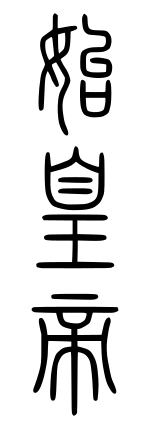
篆書体
篆書体(てんしょたい、モンゴル語:ᠭᠣᠷ
ᠦᠰᠦᠭ᠌[1]、満洲語: ᡶᡠᡴᠵᡳᠩᡤᠠ
ᡥᡝᡵᡤᡝᠨ[2] 転写:fukjingga hergen)は、漢字やモンゴル文字、満洲文字の書体の一種。「篆書」「篆文」ともいう。
広義には秦代より前に使用されていた書体全てを指すが、一般的には周末の金文を起源として、戦国時代に発達して整理され、公式書体とされた小篆とそれに関係する書体を指す。
字形の変化
金文から更に字形の整理が進み、一文字の大きさが均等になった。文字の形は天地が長い長方形の辞界に収まるように作られる。点画は水平・垂直の線を基本に、円弧をなす字画はすみやかに水平線・垂直線と交差するように曲げられる。画の両端は丸められ、線はすべて同じ太さで引かれる。
評価
上記の特徴から、金文と違って上下左右の大きさのバランスが整っており、謹厳な印象を与える文字に進化している。一方曲線を主体とするため有機的な趣きを併せ持ち、独特の雰囲気を持つ書体となっている。
また、後世の漢字のようにへんとつくり、かんむりとあしのように部首分けが容易なのも特徴である。
歴史と展開
起源
小篆の起源は、一般的には中国最古の石刻である戦国期の「石鼓文」に用いられた書体・大篆が直接の起源と言われている。「大篆」は西周の宣王の時代、太史・籀(ちゅう)が公式文字・籀文を定めた際に編纂した書物の名であると伝えられ、籀文そのものの別名であるとされている。このようなことから、石鼓文の大篆は籀文が戦国時代の秦で受け継がれたものと考えられているが、その詳細には諸説ある。
秦による公式書体化
紀元前221年、秦は中国統一を成し遂げた。この際、法治の確立や度量衡の統一の他、文字の統一が行われ、小篆が正式に統一書体として採用された。小篆は始皇帝が李斯に命じて籀文(もしくは大篆)を簡略化したもの、あるいは李斯の進言により当時の秦で行われていた籀文由来の文字を採用したものともいわれる。
始皇帝はこの小篆を権力誇示の手段として用いた。元々甲骨文の時代から文字は権力の象徴であり、それを引き継いでのものである。現に自分を讃える銘文を刻んだ「始皇七刻石」を国内6カ所に立て、大いにその権力を示した。
また小篆は秦が「統一された法治国家」であることを示すため、国の公式証明手段としても用いられた。度量衡の統一の際、決まった大きさの分銅や枡が標準器として全国に配布されたが、これに「権量銘」と呼ばれる小篆を用いた証明文が、金属製の場合直接刻み込まれ、木製の場合銅板に刻まれて貼りつけられた。また、官吏が公式証明に用いる官印にも用いられた。
こうして小篆は秦の国内政策の第一線を担う存在として扱われたのである。
隷書への展開と衰微・変質
そのような国の意図とは裏腹に、小篆はすぐにその形を崩し始める。法治国家である秦では、下層の役人が現場で事務処理を行うことが多くなった。彼らにとって複雑な形をした小篆はきわめて書きづらいものであり、自然走り書きが多く発生する結果となった。このことが小篆の書体の単純化・簡素化を生み、やがて隷書を生むことになるのである(隷変)。
紀元前206年に秦が滅亡すると、楚漢戦争を経て前漢が立った。前漢とそれに続く後漢では公式書体として小篆ではなく隷書が採用されることになったが、このことには小篆の煩雑さを避けるためという意図があった。またこのような「筆記手段」としての役割を優先した文字政策は、「権力の象徴」として存在し続けていたそれまでの文字の概念を完全に覆すものであり、甲骨文以来続いた「古代文字」の時代の終焉を示すものでもあった。
一時新代に公式書体に返り咲いたが、新の滅亡とともに再び公式書体から外され、以後しばらくの間小篆は「公的証明」の名残から官印・公印に用いられる他は、ほとんどの場合装飾的に瓦や鏡などの文様、碑や帛書の表題などに用いられるにすぎなくなる。
また後漢代の「祀三公山碑」や「嵩山三闕銘」、三国時代の呉における「天発神讖碑」「封禅国山碑」のように碑も少数ながら存在したが、いずれも天や神への願文や天のお告げを示した内容で、小篆の権力性がいつの間にか天や神に通じる性質のものへ拡大され、「神へ祈るための文字」として認識されるようになっていたことが分かる。漢代以降、小篆は、その字形や権力性から性質が変化することで、ごく一部を除いて装飾や祭祀のための特殊な文字として認識されるようになった。
そのような認識の変化がやがて文字そのものにも及ぶ。当初、漢代では秦から時代が遠くないこともあり、せいぜい隷書の書き方が入ったり線を角ばらせたりする程度の変化や崩れで済んでいた(漢篆)。しかし漢末や六朝時代以降になると完全に混沌状態になり、小篆から大量の装飾書体が生まれるなど、どんどん本来の姿から遠ざかっていくことになる。
その中でわずかに後漢代、訓詁学の第一人者の許慎が、儒学研究の一環として小篆を「古代文字」として真正面から扱い、小篆を中心とした字書『説文解字』をものして字義などの解釈をなしたが、あくまで学問的追究であり、書における展開は見られなかった。
書・印用字体としての再興
このように姿まで変化させられ、日陰者として細々と命を永らえていた小篆であったが、唐代以降再び脚光を浴びることになる。
唐の中ごろ、詩人の韓愈らが六朝の四六駢儷文を否定し古文復興運動を行った影響で、書道にも王羲之以前、すなわち隷書以前を志向する復古主義的な気運が生まれた。
そのような風潮の中、小篆は李陽冰などによって大きく注目されることになり、それまでの崩れた書法を排した、本来の姿に近い小篆による書道作品や石刻が多く使われるに至った。これにより、小篆は書道界に一書体として再興することになる。
五代十国時代の南唐および宋代には、徐鉉・徐鍇兄弟により『説文解字』の校訂・注釈が行われ、現在見られる『説文解字』のテキスト(大徐本)が作られるとともに、小篆による書道も引き継がれた。
またこの宋代以降、古印を収蔵し鑑賞する趣味が発達したことも、小篆含む篆書への関心を深める要因となった。官印、または作品の製作者や収蔵家が所有権を誇示するために押した印章には、篆書で官職名、もしくは本人の名や座右の銘を彫っているものが多かったからである。元・明代以降はこの篆書を用いた印章を彫る作業も、「篆刻」という書道の一ジャンルとして確立された。
清代においては、考証学の発達により模刻や模写を重ねている紙の法帖よりも当時の姿を留める碑の方が書蹟として信頼性が高いとの考えから、碑の研究が主流となったため、それに伴って碑しかない時代の文字であった篆書も研究・書作が再び盛んとなり、書・篆刻ともに優れた作品が残されている。また、満洲文字などの篆書もつくられた。
現代においても書作品・篆刻作品の他、「公的証明」の役割の名残として印章に用いられることが多い。
関連する書体
秦の八体・新の六体関連
許慎が著したそのままの形を伝えるテキストは存在しないが、『説文解字』序文によれば、秦では公式書体として大篆・小篆・刻符・虫書(ちゅうしょ)・摹印(ぼいん、「摹」は「募」の「力」を「手」に変えた字)・署書・殳書(しゅしょ)・隷書の8つを定めていたという(秦の八体)。許慎から700年近くが経過した残巻は、懸針体という細長い書体が使われており、これが篆書体の初期形ともされている。
また前漢を簒奪し新を建てた王莽は、公式書体制定の際にこの八体を整理、古文・奇字・篆書・隷書・繆篆(びゅうてん)・鳥虫書(ちょうちゅうしょ)の6つにしたといわれている(新の六体)。
これら秦の八体・新の六体は、いずれも何らかの形で小篆と類縁関係にある書体であった。このうち代表的なものを以下に挙げる。
大篆
秦の八体の第一に挙げられる。小篆の元となった書体で、小篆と対をなす名称。石鼓文に用いられた書体である。上述の通り、元が西周の公式文字・籀文であるという説があることから、籀文と同一視されるが詳らかではない。
字形は小篆と比べると装飾性が高く、文字全体のバランスも完全な方形ではないことが多い。金文の特徴を強く残す文字であるが、一方で画に平行部が多く見られるなど小篆の萌芽も見られる。
印篆
秦の八体に第五・摹印、新の六体に第五・繆篆として挙げる字体。その名の通り、印章用に特化した小篆のことである。現在見るような形の印篆が成立したのは漢代以降とみられる。なお、漢代に完成したため「漢篆」の一書体に数えられることもある。
縦に長い小篆を印の正方形に収めるため、小篆の曲線部分や長くはみ出す部分を直線・折線で表現したもので、有機的な形の小篆よりも角ばり、さらに整然とした印象を受ける。
鳥蟲篆
秦の八体に第七・殳書、新の六体に第六・鳥蟲書として挙げる字体。春秋時代から秦代にかけて矛など武具の装飾用に用いられた、極めて装飾性の高い書体である。
字形はうねうねと蛇のようにくねった細い線で構成される単純なもの、鳥の頭や姿を模した飾りが画の端々についているもの、さらに文字の原形を留めないほど無理矢理に鳥の形に変形させたものなどさまざまで、そのほとんどが文様化して解読不能である。
九畳篆
宋代以降の各王朝、また異民族王朝の金において官印に用いられた小篆。単に「畳篆」ともいう。小篆ないしは印篆の画を長く伸ばし、幾重にもぐねぐねと曲げて装飾性を高めた書体である。
装飾部の折れ線が印面を埋め尽くすように布字されるため、細かい線がずらずらと並んでいるようにしか見えないことが多く、判読性は限りなく低い。実用よりも官印の権威を示す役割を重視したものである。
なおこの九畳篆の登場により官印の意匠が完全に硬直化してしまい、以後の官印は書道・美術の方面からは顧みられなくなった。
新の小篆
前漢を簒奪して建てられた新では、皇帝王莽の盲目的な復古主義の影響で公式書体に小篆が採用された。秦の文字政策を模倣したもので、事実度量衡を改正の上、標準器に公式証明文「嘉量銘」を小篆で刻んで全国に配布するという秦代そのままの政策が行われている。
字形は通常の小篆の縦に細長い辞界を守りながら、一方で曲線部分を極端なまでに角張らせているのが特徴で、小篆と印篆の間を取ったような独特の雰囲気の字形になっている。線も極めて細い。
呉の小篆
三国時代の呉では、最後の皇帝孫晧の時期に「天発神讖碑(てんぱつしんしんひ)」「封禅国山碑(ほうぜんこくざんひ)」と呼ばれる小篆の碑が立てられた。
両碑の小篆は極めて特殊で、「天発神讖碑」は角ばって尖った字形でごつごつとしており、「封禅国山碑」は逆に線が非常に太くもっちりとした字体である。いずれも極めておどろおどろしい雰囲気で、後世の評価は極端に分かれている。
このような異様な字体になった理由としては、両碑が神秘思想にかぶれた孫晧の現実逃避の産物であったことが大きく関わっている。両者とも「天のお告げ」を記すための碑であり、そのために小篆の持っていた権力性が要求されたのである。
技巧上は隷書用の筆で隷書の意を含ませて書いたためこうなった、と言われているが定かではない。いずれにせよこの両者にだけしか見られない特異な小篆というべきであろう。
その他
この他にも漢代末から六朝時代にかけ、小篆の装飾性を利用して大量生産された装飾書体が存在する。
六朝時代、南朝斉の蕭子良がまとめた『古今篆隷文体』には40種類余りの装飾書体が伝えられており、小篆からの派生であると思われるものがいくつか見られる。その中の「懸針篆」と呼ばれる画の先を鋭く尖らせた書体は、『説文解字』の初期の写本「説文解字木部残巻」や空海による日本最古の字書『篆隷万象名義』にも使用されている。
同じく六朝時代の南朝梁には「百二十体書」と称して120種類もの装飾書体があったと伝えられており(書蹟が現存しないため詳細不明)、唐代には篆書を得意とした僧・夢英により「十八体書」と呼ばれる18種類の装飾書体が伝えられている。
また正倉院にも、「鳥毛篆書屏風」なる小篆の派生と思われる装飾書体で書かれた屏風が所蔵されている。
史料
小篆の史料は公式書体であった秦の時代が短かったこともあり、極端に少ない。現在残るものとしては「始皇七刻石」の一部である「泰山刻石」・「瑯琊台刻石」(ろうやたいこくせき)、そして度量衡の標準器の証明文である「権量銘」、その他木簡・竹簡がある程度である。
しかも「泰山刻石」はわずか10字が現存するのみ(拓本として十字本・二十九字本・五十三字本・百六十五字本の四種類があるが、五十三字本・百六十五字本を模刻した石から採ったものとして疑うむきもある)、「瑯琊台刻石」は86字が残っているが風雨による侵蝕で文字が涙を流したようになっており、極めて保存状態が悪い。また「権量銘」や木簡・竹簡も字形の崩れが見られ、小篆の字体を厳密には伝えていない。
このため、直接同時代の史料に当たることは極めて難しく、後世のものに頼る必要がある。幸い先述した許慎の『説文解字』には字書として基本的な文字が網羅されているので、本書に掲出する字は小篆の字形の標準として用いられている。
研究
小篆はじめ篆書は書道の書蹟として研究されるほか、漢字史の研究材料としても広く用いられている。
これは「隷変」や楷書への展開により字形が現在の形へ変化するうちに失われた、さまざまな情報を篆書、なかんずく小篆が持っているからである。これと「隷変」の過程を見たりすることでさまざまな研究が成り立つ。
たとえば「右」「左」は似ている漢字なのに、書き順は異なりそれぞれはらいと横棒を第1画目とする。楷書のままではその理由は分からないが、小篆に戻ると「右」のはらいと「左」の横棒が実は左右対称ながら同じ形をしており、第1画目であったことが分かる。それらが「隷変」の過程でそれぞれはらいと横棒という別の形に変化してしまったために、現在のような書き順になってしまったと説明出来るのである。
ただし正確な研究には、篆書以前の甲骨文や金文の情報も必要になる。既に篆書以前の段階で失われた情報も多いからである。事実許慎の『説文解字』は、甲骨文や金文の知識がなかったためにさまざまな間違いを起こしている。
現代における篆書体
利用実態
前述の通り、小篆は現代でも書道や印章の世界では現役の書体である。
身近な例でいえば、日本銀行券の表の「総裁之印」、裏の「発券局長」の印章の文字がある。曲線が多く判読も容易ではない印章の朱い文字の書体である[3]。これは明治時代に篆刻家の益田香遠に作らせたものである。 また旅券の表紙の「日本国旅券」の文字や、郵便切手の「日本郵便」の文字や自治体の印章などのほか一部の店の看板に使用されている程度であったが、最近では字形の面白さから装飾文字やデザインとしても用いられることも多くなっている。
このことから昨今の時流に乗って小篆を取り入れた「篆書体フォント」がいくつも作られるなど、デジタルの世界にも進出を果たしており、比較的気軽に小篆を使用出来るようになった。
従来は手彫りによっていた小篆の印章作成も、これらのフォントを用いることで比較的安価に素早く出来るようになっている。
問題点
このようにデジタル時代になり、コンピュータの恩恵にあずかる形で日常生活の中に進出してきた小篆であるが、進出の主な媒体が「篆書体フォント」という「フォント」であるゆえの問題点もある。
伝統的小篆との衝突
書道用・篆刻用書体としての小篆は『説文解字』などしかるべき文献が基準にあり、字形が大きく現状と異なっても手を加えることはしない。また当時存在しなかった字は、相当する別字で代用するのが普通である。
造字行為はよほどの理由がない限り避けるべきとされ、現在も「絶対にやるべきではない」「やむを得なければやってもよい」「こだわらず自由にやってもよい」と人によって許容範囲が大きく異なるデリケートな問題となっている。
一方、篆書体フォントは字形に対してはかなり自由であり、『説文解字』の字形を基準とすると「間違い」とされるような字形が通用していることが少なくない。
また他の小篆の字や隷書・楷書の形を参考にしたり、仮名を小篆風に仕立てるなどして大量の造字を行い、「楷書風の小篆」「新字体の小篆」「仮名の小篆」「アルファベット・アラビア数字などの小篆」などといった歴史的に有り得ないはずの文字を生み出している。
一見すると篆書体フォントの制作態度はいい加減であるように思えるが、そう解釈すべきではない。篆書体フォントはあくまでパソコン用のフォントであるため、その制作は「デザイン」としての側面を持ち、『説文解字』のような一つの基準に縛られる必然性が必ずしもあるわけではない。
また実用書体として作られているため、字形が全く現在の書体と似ても似つかなかったり、また字そのものがないなどの現象が多発する篆書体そのままを使用することは出来ない。また姓名・会社名を記す以上、日本独自の字形・文字である新字体や仮名に対する対応も必要になる。伝統と歴史を重視する書道用・篆刻用書体の小篆とは、立場も存在目的も異なるのである。
このようなことから「篆書体フォント」はあくまで小篆のデザインを実用本位で模倣した一種の装飾フォントであり、伝統的な「小篆」とは違う。
印影の画一化
篆書体フォントは先述のように小篆による印章作成を容易にしたが、逆に誰でも同じフォントを買って導入することが出来るようになったため、全く違う店で彫ったにもかかわらず印影が同じ、という事態が発生している。
このことは小篆を用いた印章の証明性を下げる事態にもなりかねず、将来的に問題となる可能性がある。
様々な篆書の文字